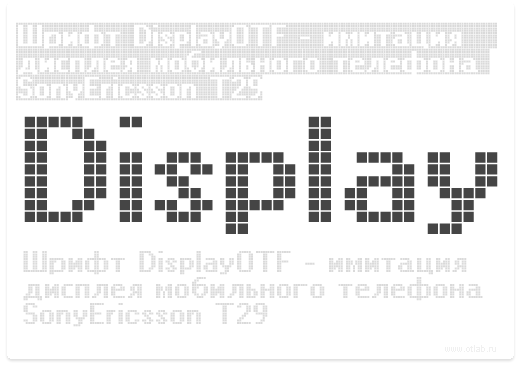
Шрифт DisplayOTF
Имитация шрифта дисплея сото­вого телефона в стандартном и активном состоянии. По мотивам телефона SonyEricsson T29. Ри­сунок знаков выполнен таким об­разом, что бы умещаться в одну строку. Выделенное сос­то­яние дисплея подключено в качестве альтернативного на­чер­та­ния, по средством скрип­та (фичи) 'salt' (Stylistic alternates). Скачать [url=http://otlab.ru/fonts/displayotf.html]шрифт DisplayOTF[/url]